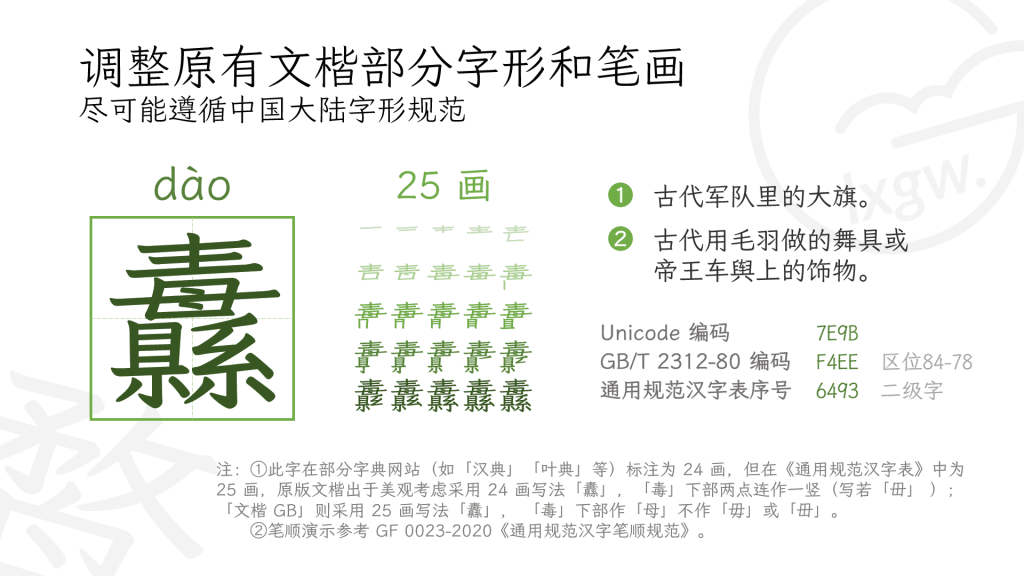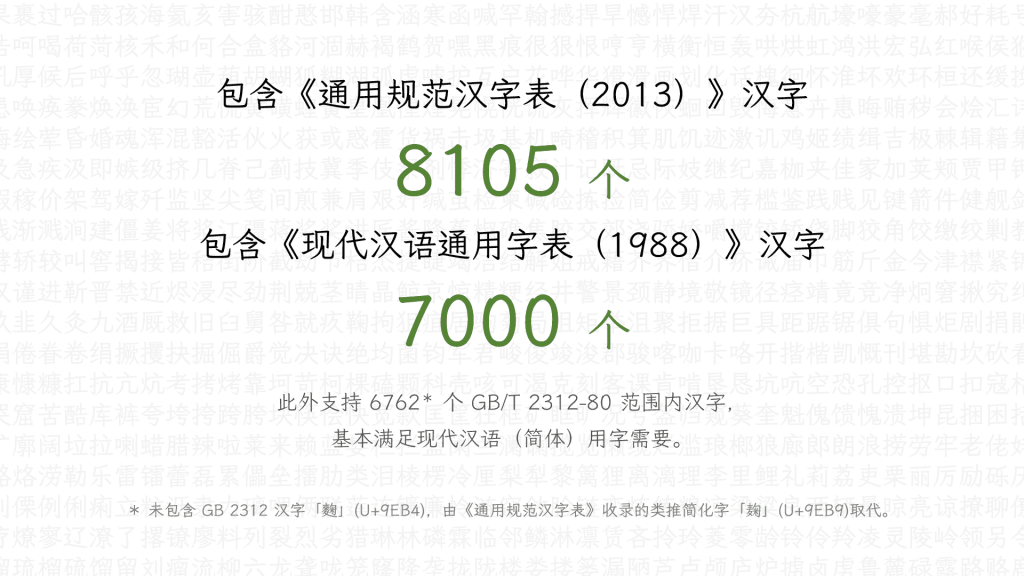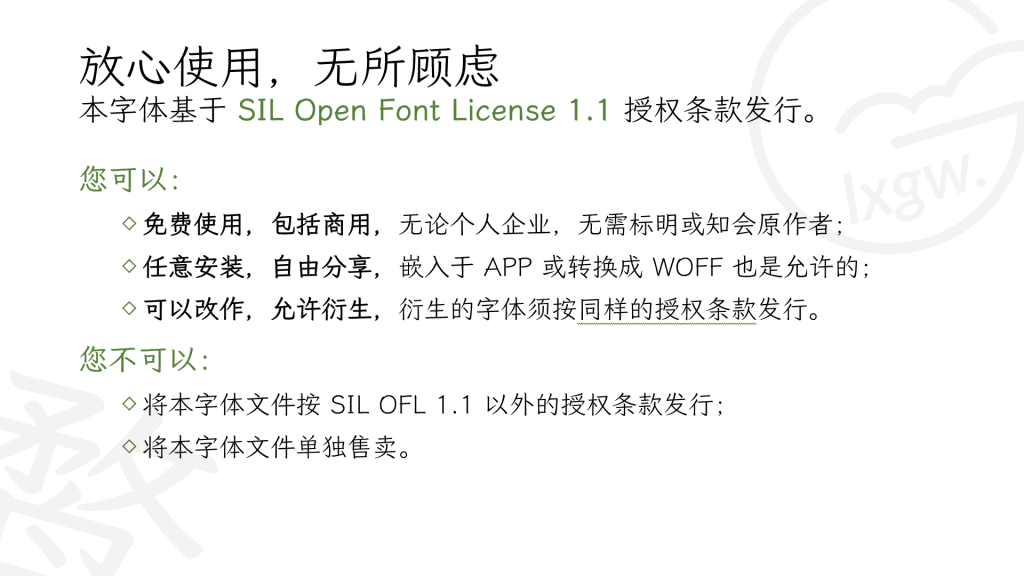
2020 年 12 月,日本著名字体厂商 FONTWORKS 在 GitHub 上释出了 7 款开源日文字体,其中 Klee One 字符数最多,兼有仿宋和楷体的特点,具有优雅的外观及温润的阅读感。与一般的教科书体相比,Klee One 保留了传统印刷字体的一些特征。2021 年,本人在其基础上增补和修改字形,制成「霞鹜文楷」/ LXGW WenKai 字体,受到广泛欢迎。除此之外,一些字体爱好者也制作了其他的衍生版本,如「芫荽」/ Iansui 等。
虽然「霞鹜文楷」修改了 GB/T 2312-1980 及《通用规范汉字表》范围内的汉字字形,使其接近中国大陆推行的新字形,但仍保留了 Klee One 印刷体的特征,如「亠」「宀」等起笔的直点,「㇙」「㇜」等笔画折角处断笔设计等,因此一些人认为「霞鹜文楷」的字形并不规范,不是「G 源字形」,不符合一般楷体的书写习惯。鉴于此,本人在「霞鹜文楷」的基础上,尽可能严格按照中国大陆的字形标准(G 源字形)对字形、笔形作进一步修改,继续沿用「霞鹜文楷」名称,增加「GB」后缀表示字形遵循国标。由于 Klee 字体的 Regular 字重太细,故选取原字体 SemiBold 字重作为本字体的 Regular 字重。
本字体目前收录了《通用规范汉字表》(2013)的 8,105 个汉字、《现代汉语通用字表》(1988)的 7,000 个汉字,以及 GB/T 2312-1980 的 6,763 个汉字,并视需求补充了部分较常用的其他汉字(详见「外字初步整理一览表」),基本满足现代汉语(简体字)的日常使用需求,适用于对规范字形要求较高的场合(但可能并不适合义务教育图书、少儿读物、字帖等对规范字形要求极高的场合)。
自 v1.0 版本起,依照「繁异体及其他外字初步整理一览表」新增繁体字及 IICore 汉字支持;自 v1.320 版本起,补全 CJK 统一汉字基本区和扩展 A 区的完整字符集,符合 GB 18030-2022 实现级别 2 的收字范围。
- 本字体的调整主要参考《通用规范汉字表》及教育部规范 GF 0023-2020《通用规范汉字笔顺规范》,并结合其他遵循国标的楷体、仿宋字形(如「教材规范楷体」),尽可能消除 Klee One 原有的「直点」「断笔」等传统印刷体特征,使字形更符合楷体书写习惯。但受个人审美、时间及工作量等因素影响,仍保留少量与规范楷书字形存在差异的细节,作为风格处理。例如,围字框「囗」等部件因涉及字形较多,保持 Klee 原有风格,未作改动;此外,限于 Klee 字体自身风格,本字体不区分「悬针竖」与「垂露竖」。因此,本字体可能并不适合义务教育图书、少儿读物、字帖等对规范字形要求极高的教育场合。
- 小写字母 l 调整为原 Klee One 的直棍写法,以符合汉语拼音书写习惯;大写字母 I 调整为两端有横杠的写法,以与小写字母 l 区分。
- 另提供「彭蠡文楷」,根据《GB/Z 40637-2021 古籍印刷通用规范字形表》收字和调整字形
(真·国标繁体)。
霞鹜文楷 GB: 这个字体的细体,只要不是要求特别严格的公文或者教育行业使用场景,几乎都可以用作 仿宋 的替代字体。用心了!
这款字体的大写“I”加上了两道横杠,小写“l”去掉钩,可能是因为更符合汉语拼音的字形标准
是这样的,不过介绍里没写。